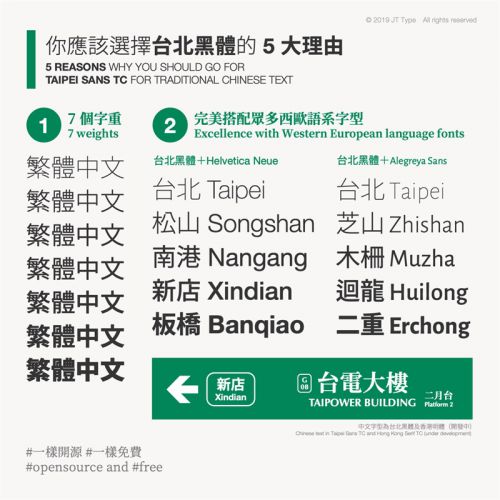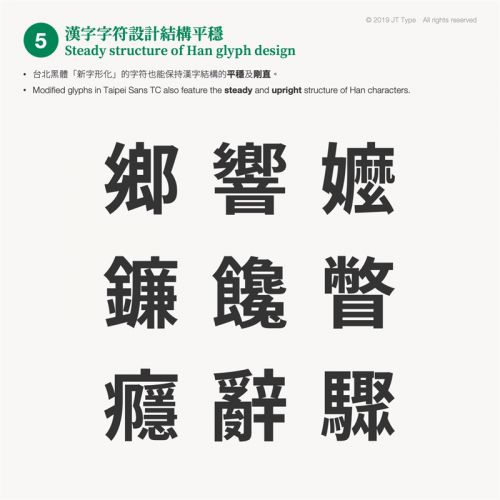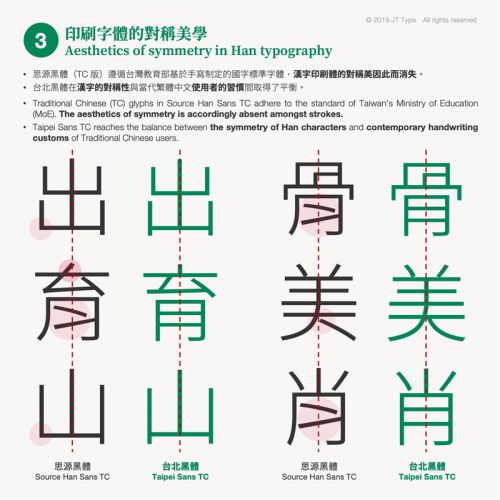
台北黑体
台北黑体是一款现代简约风格的黑体字体,以清晰利落的字形设计成为黑体家族中兼具实用性与美学感的细字重代表。其整体造型方正端庄,在保留黑体核心特征的同时,通过细腻的笔画处理,展现出独特的轻盈气质,适用于标题设计、品牌VI、平面广告等多元场景。 台北黑体的字形结构极具辨识度:方正的字型形态搭配居中的字体重心,中宫比例适中,确保文字在不同字号下均能保持良好的可读性。无论是大标题的醒目呈现,还是正文的连续排版,都能传递出稳定、专业的视觉感受,避免阅读疲劳。 在笔型设计上,台北黑体采用利落的直角处理,笔画以方头收尾,线条粗细均匀,配合笔画间的断开设计,既强化了现代科技感,又让整体造型更显透气。这种“简而不减”的设计语言,使字体在信息传达时兼具精准度与艺术感,尤其适合需要突出简洁、时尚调性的设计项目。 作为免费商用字体,台北黑体覆盖常规中文字符集,满足多数设计需求。无论是电商Banner的吸睛标题、新媒体配图的文字搭配,还是书籍装帧的内文排版,台北黑体都能以简约而不简单的风格,为作品注入现代美学气息,是设计师日常创作的实用之选。